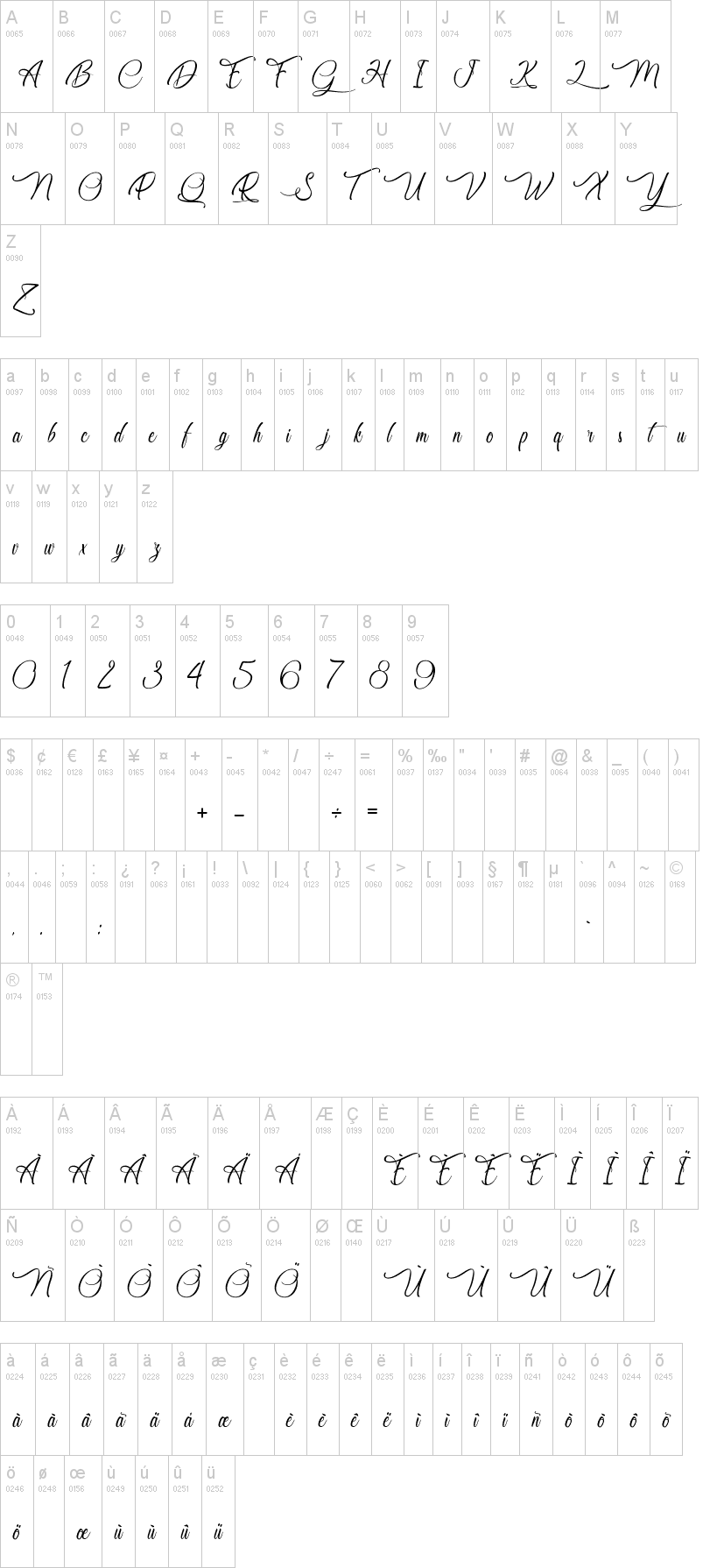
Chocolatines
Chocolatines 是一种手写风格的字体,由设计师 Joël Carrouché 创造。这是一种装饰性字体,具有流畅和优美的曲线,字形中有许多精致的细节,适合用于卡片、海报、包装和其他设计项目。 这种字体有两种版本,普通和粗体。它们都具有相同的设计风格,但粗体版本的字体线条更加粗壮,并且更加醒目。Chocolatines 字体具有良好的可读性和易用性,可以用于许多不同的设计项目,以增强它们的视觉吸引力。
Chocolatines是一款非常不错的手写艺术字体,具有很好的视觉感,适合于文化类的宣传设计、商业类品牌的广告和产品包装设计以及个性化文字排版等较多场景。
Chocolatines字符映射图